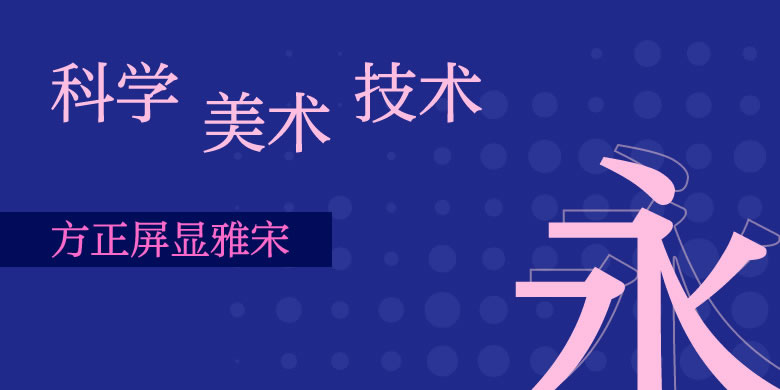
方正屏显雅宋
方正屏显雅宋,这款字体结构工整、笔画清晰,兼顾美观与易读性,适用于标题、正文、海报、包装、LOGO 等多种场景。字形优雅稳定,风格百搭耐看,适配日常排版与创意设计,让文字呈现更舒适、更具质感。方正屏显雅宋一笔一画,皆是细节,以均衡的比例、流畅的线条打造舒适视觉体验,字形端正大气,风格简约现代。无论是商业设计、品牌宣传还是日常排版,都能轻松驾驭,让文字更有格调与力量。方正屏显雅宋字体下载。
字体品牌: 方正字库 设计师:朱志伟 字体分类:宋体、创意字体 字体属性:精品字 字符集:大陆简体(GB2312-80)、简繁扩展(GBK) 发布时间: 2017
屏显雅宋是在标雅宋基础上的针对屏幕应用的改良设计版。雅宋家族是字重梯度多、设计质量高的宋体家族之一,曾获得“亚洲最具影响力设计大奖优秀设计奖”。其中标雅宋适合正文排版,但原先的设计着眼于纸质印刷,直接运用于屏幕上,则显得横竖差别偏大,对屏幕阅读的舒适度有一定的影响。为此,重新设定了横竖比例,并做了一些局部改良,使得在屏幕应用中有良好的表现。